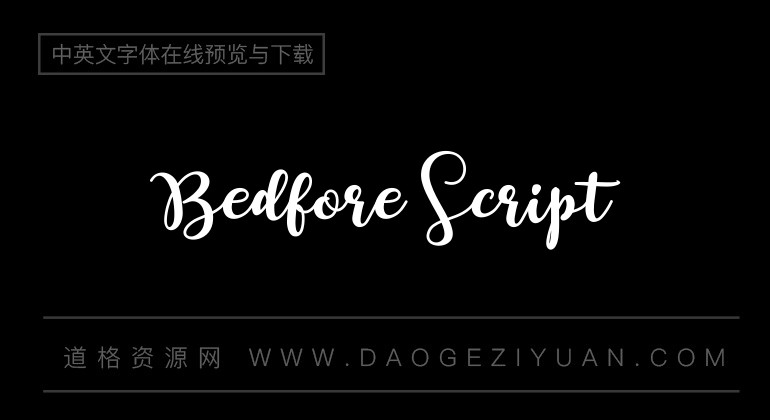
Bedfore Script 是一款优雅、风格独特的手写字体,其笔画流畅,字母间距适中,适合用于印刷品、海报设计、商业品牌等多种场合。 Bedfore Script 字体的特点是带有一定的仿古风格,每个字母都有饱满的笔画,线条流畅自然。它的笔画略微偏粗,使得字母看起来更加清晰、易读。此外,Bedfore Script 字体还具有一定的可读性和美感,特别适合用于品牌标志、海报等场合。 Bedfore Script 字体可用于多种设计领域,例如印刷品、海报、标志、商品包装、T恤和其他纸制品设计。如果您正在寻找一款独特而优雅的手写字体,Bedfore Script 是一个不错的选择。内容介绍
Bedfore Script是一款非常不错的手写艺术字体,具有很好的视觉感,适合于文化类的宣传设计、商业类品牌的广告和产品包装设计以及个性化文字排版等较多场景。